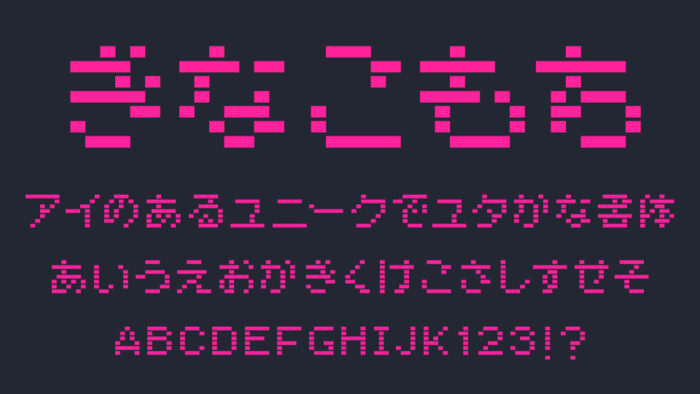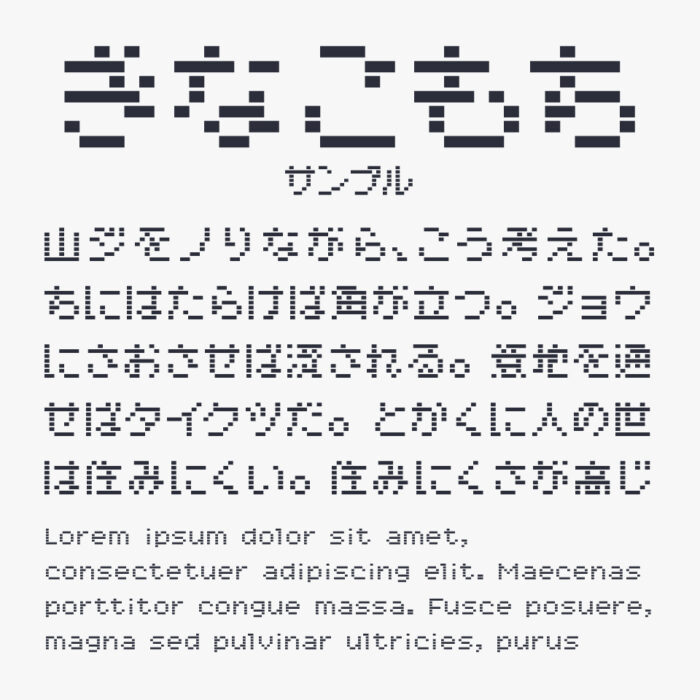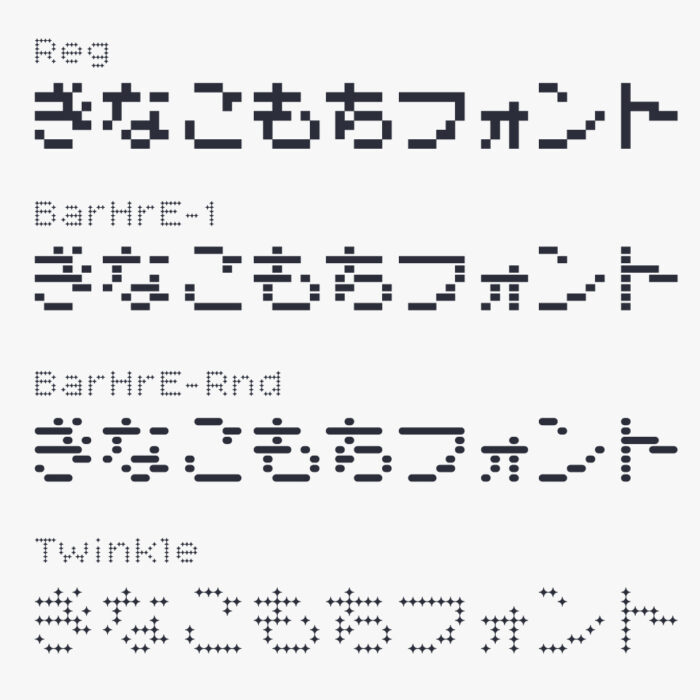
Nu きなこもち
きなこもちフォントは、8×8のピクセルで制作されたレトロデジタル感が楽しい、ユニークで遊び心のあるピクセルフォントです。
ファミコンなどの8bitのレトロゲームの雰囲気のような味わいがあるフォントです。全体的に「ふっくら」とした丸みが特徴的なピクセルフォントとなっています。
ピクセルの形が異なるバリエーションが58種類用意されているのも驚きのフォントです。サンプルでは4種類のみご紹介となりますので、すべて見てみたい方はぜひ配布サイトをご確認ください。
本記事で、上記のサンプルでは「BarHrE-1」のスタイルを使用しています。ドットが横に繋がっているようなデジタル感の感じるフォントとなっています。